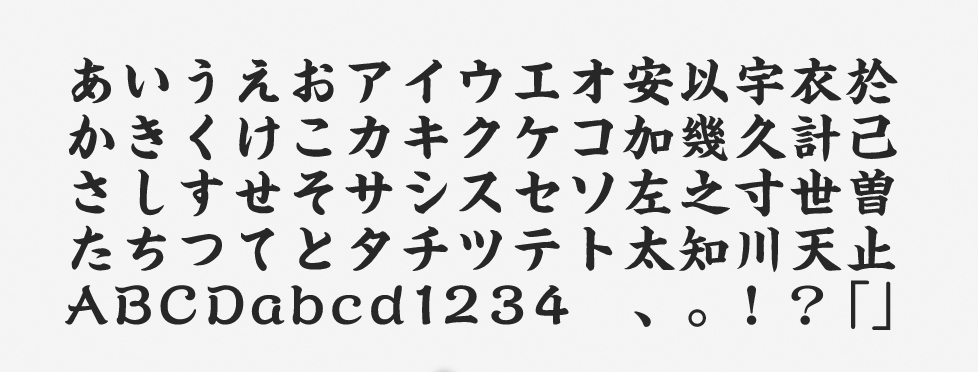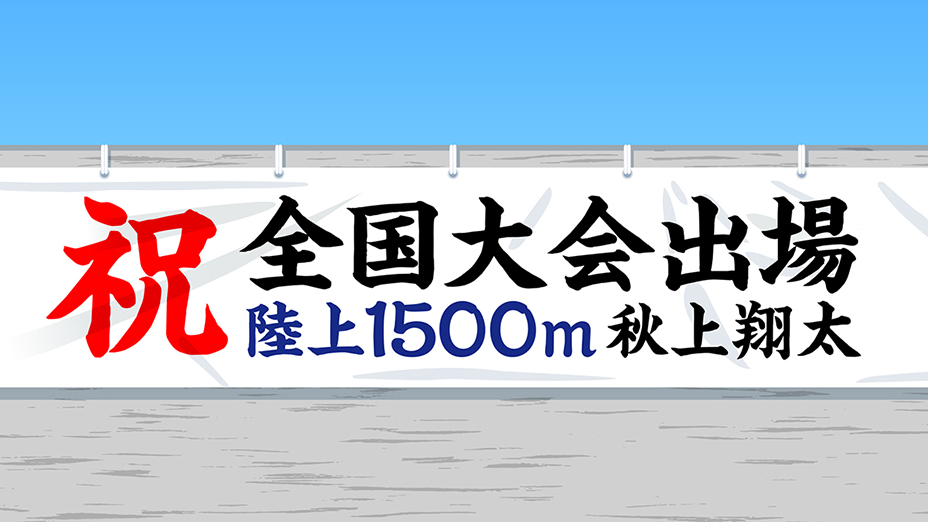
「楷書MCBK1」について
楷書体は5〜7世紀の手書きの楷書に起源を持つフォントです。点画がはっきりと書かれた正式な書体で、フォーマルなシーンによく似合います。その性質上、すっきりとしたイメージのフォントが多いですが、楷書MCBK1は従来の楷書の印象とはまた趣が異なる極太の楷書体です。どっしりとした安定感や、力強いインパクトがあります。
「楷書MCBK1」の特徴
正統派で堅実な印象と、重厚な筆づかいを兼ね備えているのが楷書MCBK1です。独特の存在感で見る者を惹き付けるため、主張の強いキャッチコピーや見出しなどで使うと特に効果的です。
それぞれの字面の大きさが揃えられているため、整理された印象を与えやすいことも特徴。縦組みでも横組みでも違和感なく使えるフォントです。クセの少ない漢字などに比べ、従属欧文(英数字)はやや個性的な雰囲気も感じさせます。
学校に掲出される垂れ幕を想定したグラフィックで、堅実な印象の楷書MCBK1を使用しています。今回のような比較的にフォーマルなデザインには、このフォントが似合うでしょう。文字列は両端揃えにして整え、かっちりとした印象を強めています。